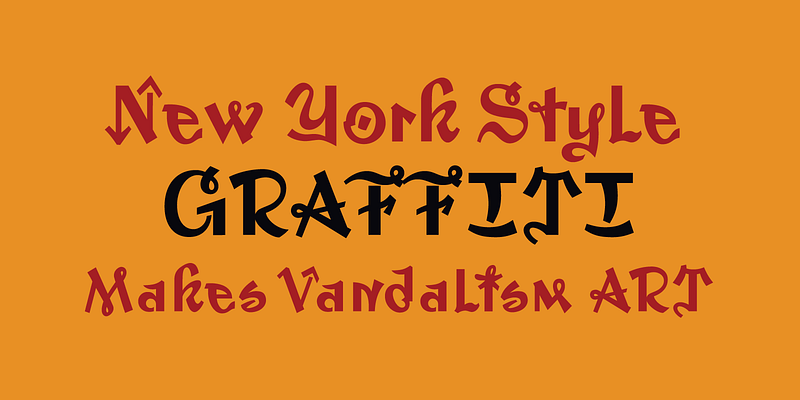
À la fin des années 70, Leslie Cabarga a recueilli des échantillons de graffiti sur les murs de New York. Il en a étudié les tendances communes pour unir l’énergie par ailleurs contradictoire des différents graffitis. Les conceptions sont restés invisibles pendant dix ans jusqu’à ce que le Macintosh fournisse l’outil que Cabarga souhaitait. Il a alors transformé ce contenu fascinant en une police de caractères cohérente, Graffiti, conçue pour Font Bureau. ; FB 1993
Zavier Cabarga a dessiné des images et des caractères toute sa vie. « Le dessin exige une perception inhérente de l’anatomie et de la proportion. Il en va de même pour la typographie, car je crois que nos anciennes lettres sont basées sur les proportions humaines », explique Zavier. « C’est d’abord les bandes dessinées qui m’ont inspiré, puis j’ai commencé à copier des logos et des caractères de titrage que je trouvais dans des magazines. À 15 ans, j’ai décapé des négatifs pour former une police de photocomposition brute mais utilisable. »
Travaillant sous le nom Handy Lettering Co. pendant de nombreuses années, Zavier a créé des caractères à la main pour des clients du secteur de la publicité tout en travaillant à temps plein comme illustrateur. « Dessiner des illustrations a toujours semblé difficile, alors qu’écrire, c’est facile et amusant », explique Zavier. « Je travaille depuis 25 ans sur Macintosh, ce qui m’a permis de créer des polices d’ordinateur, ce qui, à bien des égards, est la chose la plus satisfaisante que je fasse. Taper une lettre ou un caractère manuscrit avec une police que j’ai créée me donne l’impression d’être Dieu ».